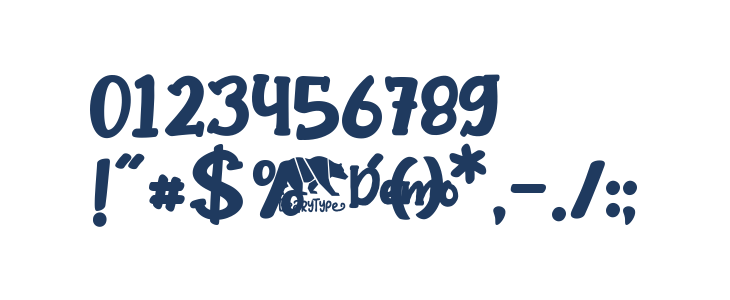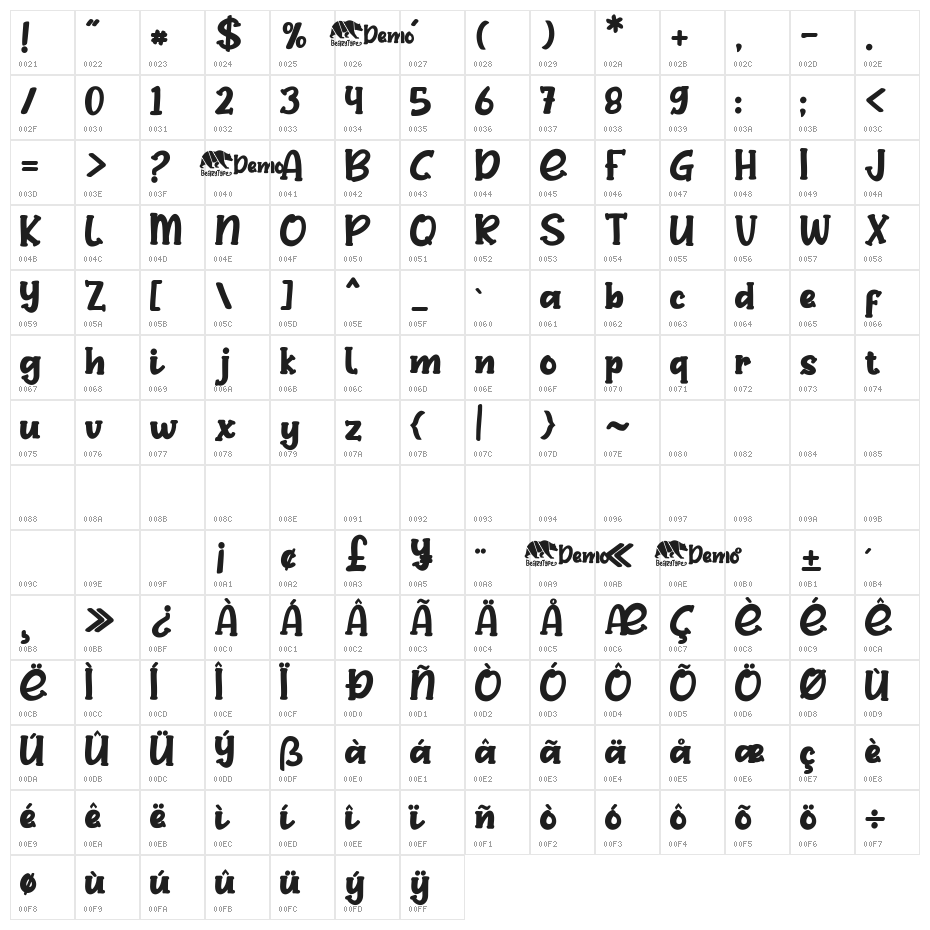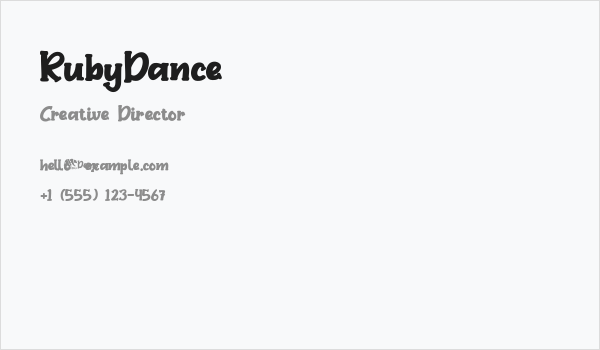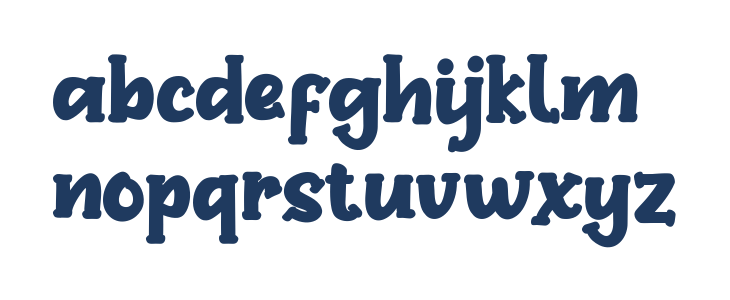
RubyDance Font
✎ Cartoon
| Kategorien | Cartoon |
| Gesamtstil | Playful, Casual |
| Vorgeschlagene Projekte | Ideal for children's books, playful branding, greeting cards, and creative posters. |